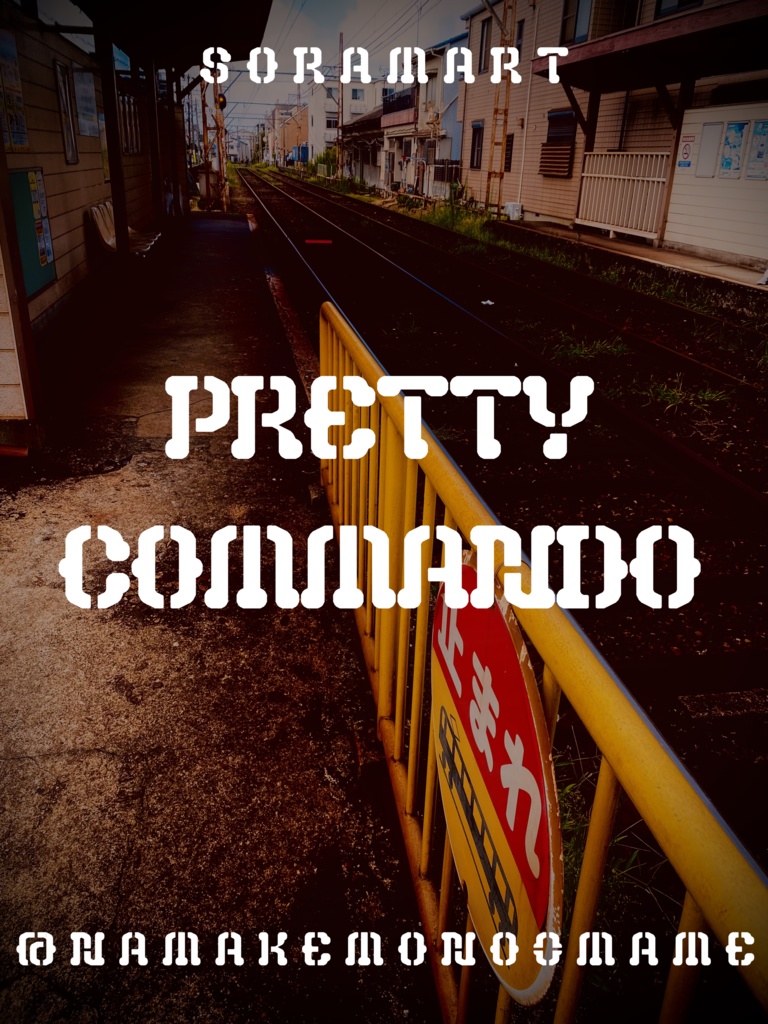
そらマートフォントデータ”Pretty Commando”Digital2,500 JPY카트에 담기기프트 보내기About Gift丸っこいシルエットの、かわいらしいステンシル調フォント "Pretty Commando" です。 「TrueTypeフォントファイル」という形式です。 ダウンロードした後、Zipファイル内のデータをインストールしてお使いください。 このフォントは商用利用可となっております。 お客様の制作・創作活動のお役に立てれば幸いです。 ※使用上の注意事項などは、添付のReadmeをお読みください。そらマートVisit FANBOX!Fontsフォントデータ”Tonik Crate”そらマート0 JPYFontsフォントデータ”Vapor Sprout Edge”そらマート2,500 JPYFontsフォントデータ”Vapor Sprout Wide”そらマート2,500 JPYFontsフォントデータ”Vapor Sprout”そらマート2,500 JPYFontsフォントデータ”Star Shoot Ray”そらマート2,500 JPYFontsフォントデータ”Star Shoot Black Wide”そらマート2,500 JPYFontsフォントデータ”Star Shoot Black”そらマート2,500 JPYFontsフォントデータ”Mars Invader Balloon”そらマート2,500 JPYFontsフォントデータ”Mars Invader Wide”そらマート2,500 JPYFontsフォントデータ”Mars Invader”そらマート2,500 JPYFontsフォントデータ”Rock Cut Serif”そらマート2,500 JPYFontsフォントデータ”Rock Cut Drop Wide”そらマート2,500 JPYFontsフォントデータ”Rock Cut Drop”そらマート2,500 JPYFontsフォントデータ”Longtail Sans Serif Slashed”そらマート2,500 JPYFontsフォントデータ”Longtail Sans Serif Bold”そらマート2,500 JPYFontsフォントデータ”Longtail Sans Serif”そらマート2,500 JPYFontsフォントデータ”Abyss Dive Punk Retro”そらマート2,500 JPYFontsフォントデータ”Abyss Dive Punk Wide”そらマート2,500 JPYFontsフォントデータ”Abyss Dive Punk”そらマート2,500 JPYFontsフォントデータ”Emerald Sphere Sprite”そらマート2,500 JPY더보기